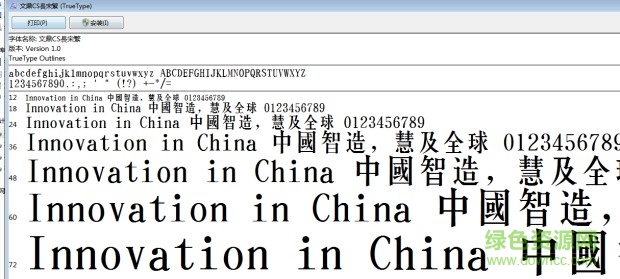
文鼎cs長宋繁字體是文鼎字體中的一種哦,這款字體字形粗細適中,并且字形也是非常美觀,適用的場合也是超級廣泛的哦,有需要的朋友趕緊來綠色資源網(wǎng)下載吧!
文鼎CS長宋繁字體,是一款方正型繁文字體,字庫中數(shù)據(jù)全面,字體繁體設(shè)計更有古樸之美,可以用于適合繁體的ps字體、海報設(shè)計素材等等